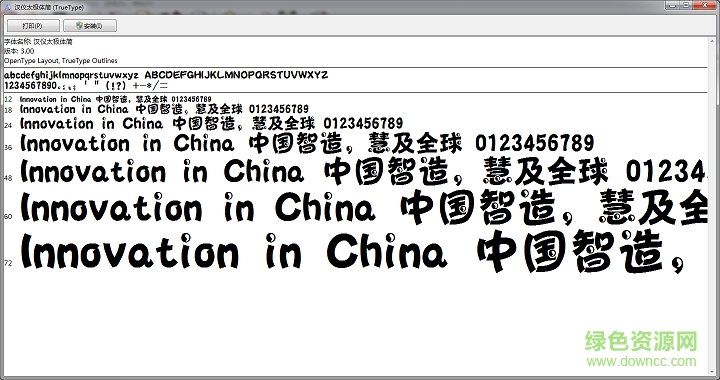
軟件介紹 軟件標簽: hyo3gj 漢儀字體 hyo3gj是什么字體?hyo3gj字體就是漢儀太極體簡字體,字體清晰,胖而不臃,變化得當,筆畫較粗略圓潤,顯得十分可愛,喜歡的小伙伴快來綠色資源網(wǎng)下載吧!hyo3gj字體安裝說明方法一:控制面板/字體/文件/安裝新字體;方法二:直接將字體復制到C:\WINDOWS\Fonts。hyo3gj字體特點hyo3gj是一款比較有特色的可愛字體,字體的點是一個太極符號,字體總體看起來是一款偏向于可愛類型的字體,應該比較適合女孩子使用的。 軟件截圖 上一張下一張(1 / 1) 安裝詳細截圖 猜你喜歡 漢儀字體 漢儀字體 漢儀字體有哪些?漢儀字體下載大全收錄了所有好看的、經(jīng)典的漢儀字體合集,漢儀字體是由北京漢儀科印信息技術(shù)有限公司創(chuàng)作,這些字體種類齊全,各具特色、應用領(lǐng)域廣泛,喜歡漢儀字體的朋友歡迎來綠色資源網(wǎng)免費下載使用! 查看更多>> 阿里巴巴普惠字體 26.00M/中文/0.8/官方ttf版下載 漢儀天宇風行體 21.41M/中文/5.0/下載 漢儀蘇澤立行楷精修版簡 3.01M/中文/4.0/免費版下載 漢儀正圓(共7款) 17.96M/中文/2.8/ttf免費版下載 漢儀可愛字體打包 41.20M/中文/5.0/14款下載 漢儀曉波花月圓字體 1.89M/中文/0.0/下載 其他版本下載 標題 大小 更新日期 下載 下載地址 電腦版 hyo3gj字體 點擊報錯 軟件無法下載或下載后無法使用,請點擊報錯,謝謝! 關(guān)閉報錯反饋 請描述您所遇到的錯誤,我們將盡快予以修正,謝謝! *必填項,請輸入內(nèi)容 本類最新 漢儀孟瑞體ttf v1.0 官方版 漢儀字庫免費 132款 阿里巴巴普惠字體 官方ttf版 漢儀字體打包大全 for Mac 蘋果電腦版_ 共131款字體 漢儀純愛情書拼音體 ttf版 漢儀北魏寫經(jīng)w字體 免費版 相關(guān)文章 Photoshop字體安裝使用方法和技巧 電信天翼3G無線上網(wǎng)卡的安裝方法 rhythmbox 亂碼的解決方法 windows7字體顯示問題:打開某些程序的時候顯示的是亂碼 Windows7安裝字體和用快捷方式安裝字體 諾基亞5320XM改變手機QQ和飛信字體大小的方法 用戶評論 熱門評論 最新評論 發(fā)表評論 查看所有評論(0) 昵稱: 請不要評論無意義或臟話,我們所有評論會有人工審核. 字數(shù): 0/500 (您的評論需要經(jīng)過審核才能顯示)